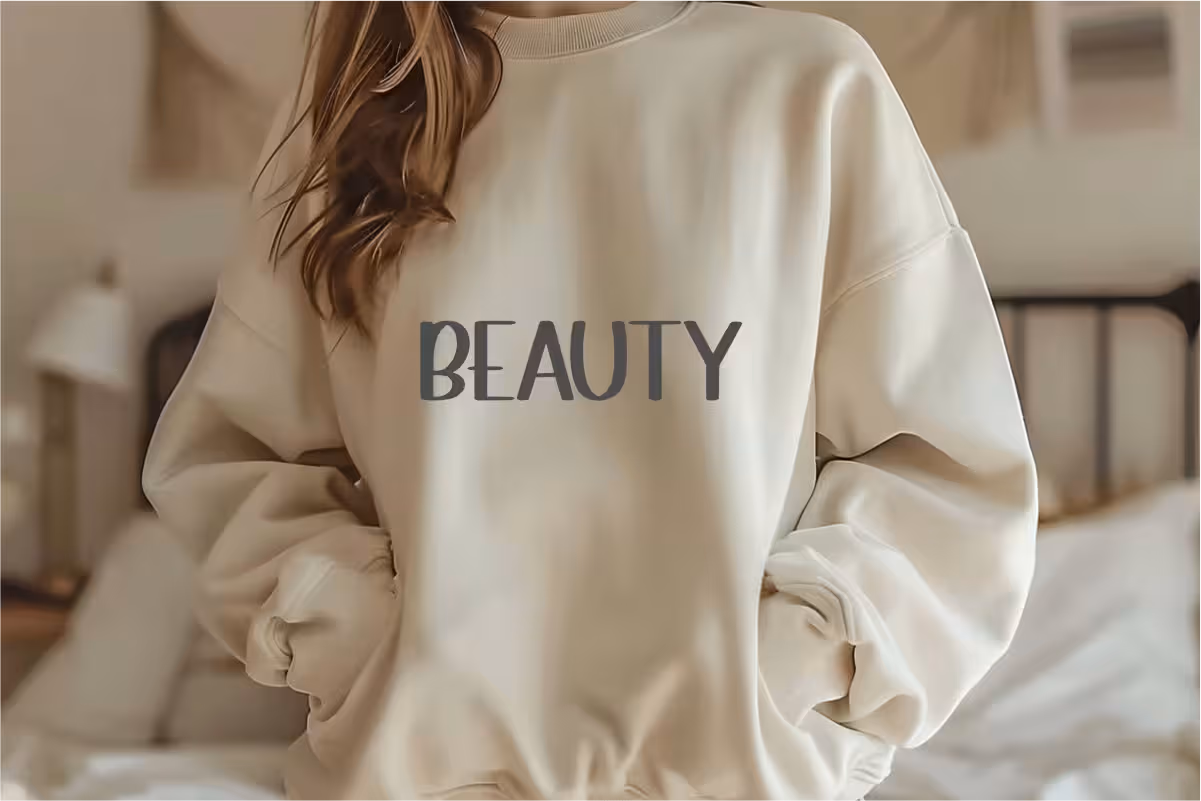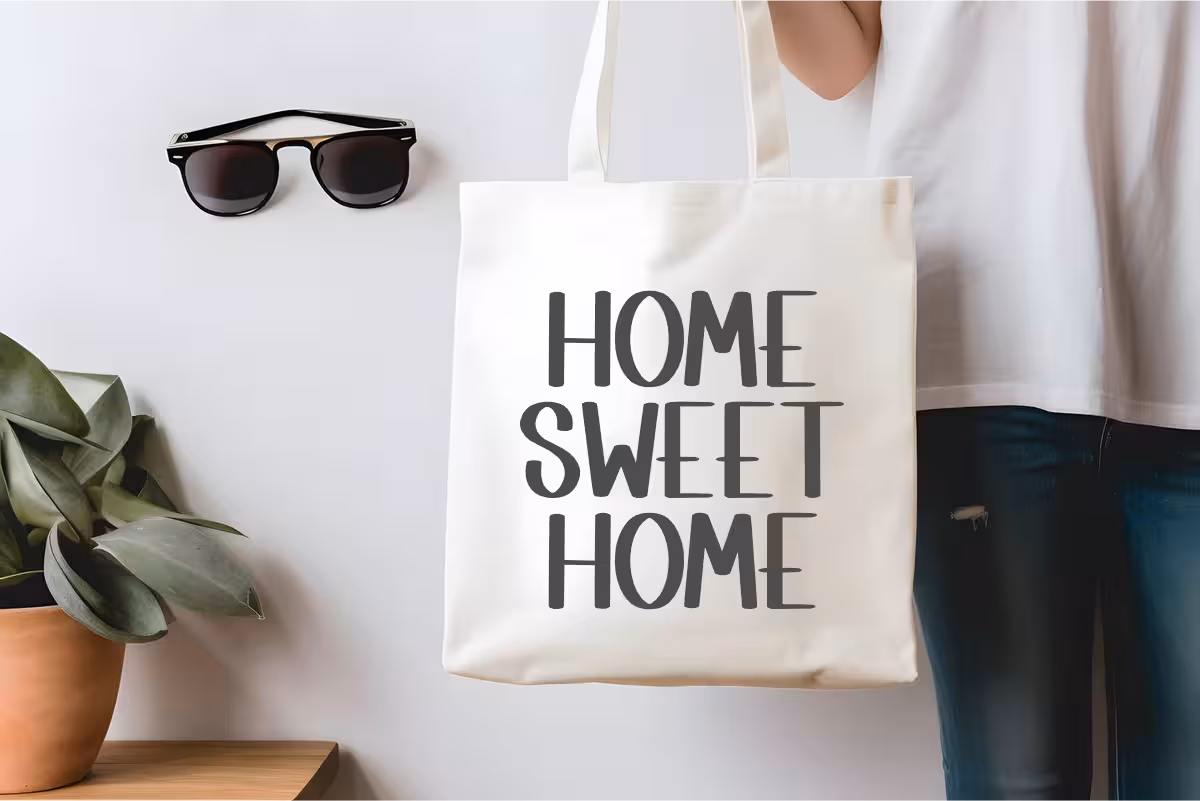
Giới thiệu về Font TF Smart Teacher Việt hóa
TF Smart Teacher Việt hóa là một font chữ nổi bật với thiết kế cao, bo tròn mềm mại và đầy đặn, mang đến vẻ ngoài thân thiện, thông minh và cực kỳ đáng yêu. Font này gợi cảm giác về sự gần gũi, hồn nhiên nhưng vẫn rất rõ ràng và dễ đọc, lý tưởng để tạo điểm nhấn độc đáo và thu hút sự chú ý một cách tinh tế.
Với đặc điểm hình dáng độc đáo, cao, tròn và phong thái dễ chịu, Smart Teacher là lựa chọn lý tưởng cho các thiết kế muốn truyền tải sự vui tươi, sự thoải mái và sự gần gũi:
- Thiết kế túi vải canvas: Hoàn hảo để in các câu trích dẫn, slogan, họa tiết chữ hoặc hình ảnh minh họa lên túi vải canvas. Nét chữ bo tròn dễ thương và rõ ràng của font sẽ làm cho chiếc túi trở nên cá tính, thân thiện và thu hút sự chú ý một cách đáng yêu. Đây là lựa chọn tuyệt vời cho các thương hiệu thời trang hướng đến phong cách trẻ trung, giản dị hoặc các sản phẩm quà tặng.
- In áo thun: Lý tưởng để in các thông điệp, tên nhóm, hoặc hình ảnh chữ lên áo phông, áo hoodie. Font này sẽ giúp áo thun trở nên nổi bật, phong cách và truyền tải thông điệp một cách dễ thương.
- Thiết kế cốc/ly: Phù hợp để in các câu nói, hình ảnh chữ lên cốc, ly sứ, hoặc các vật phẩm lưu niệm. Nét chữ thân thiện của font sẽ làm cho sản phẩm trở nên cá tính và là món quà ý nghĩa.
- Thiết kế cho giáo dục và trẻ em: Rất thích hợp cho các ấn phẩm liên quan đến giáo dục, trường học, sách vở, hoặc các tài liệu dành cho trẻ em, giúp tạo không khí học tập vui vẻ và thân thiện.
Với TF Smart Teacher Việt hóa, bạn có thể dễ dàng thổi hồn vui tươi, đáng yêu và sự tươi mới vào các thiết kế, tạo ra những sản phẩm không chỉ đẹp mắt mà còn đầy cảm xúc và sức hút, đặc biệt hiệu quả cho các dự án cần sự mềm mại và thân thiện.
Font Việt hóa TF Smart Teacher